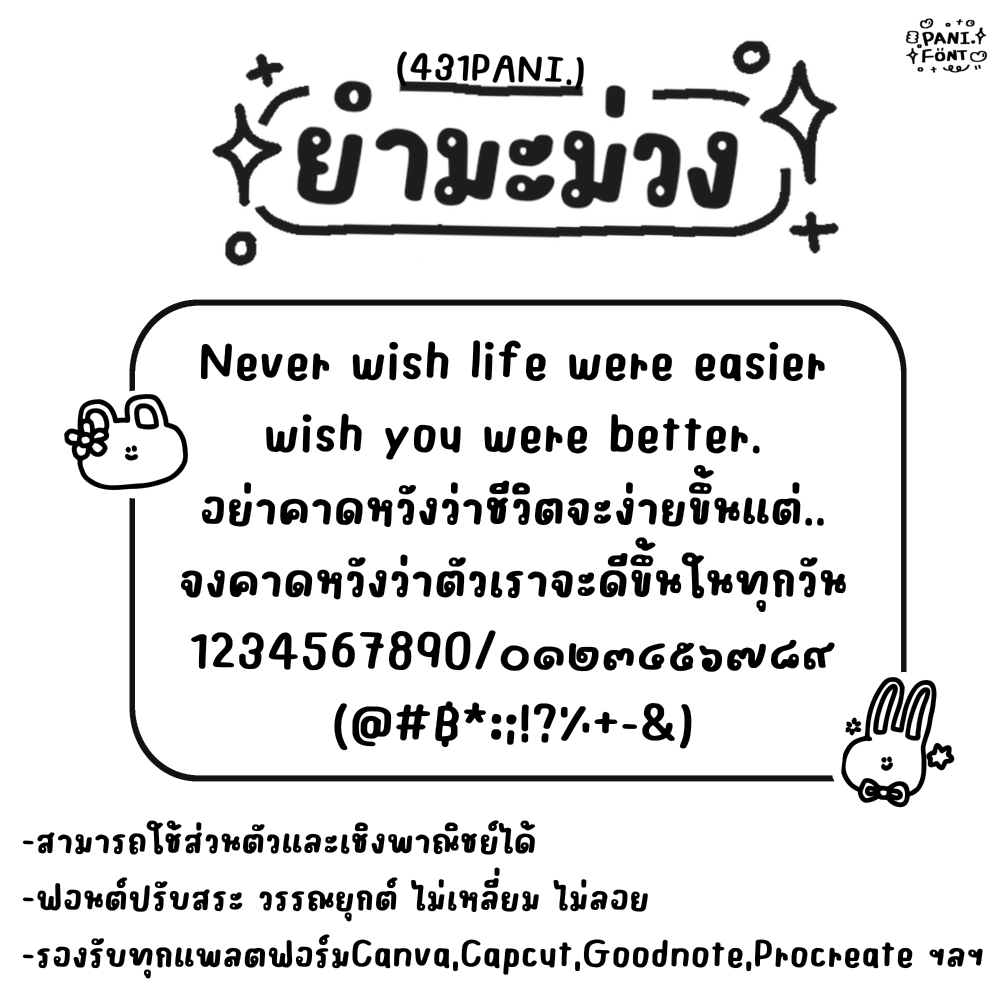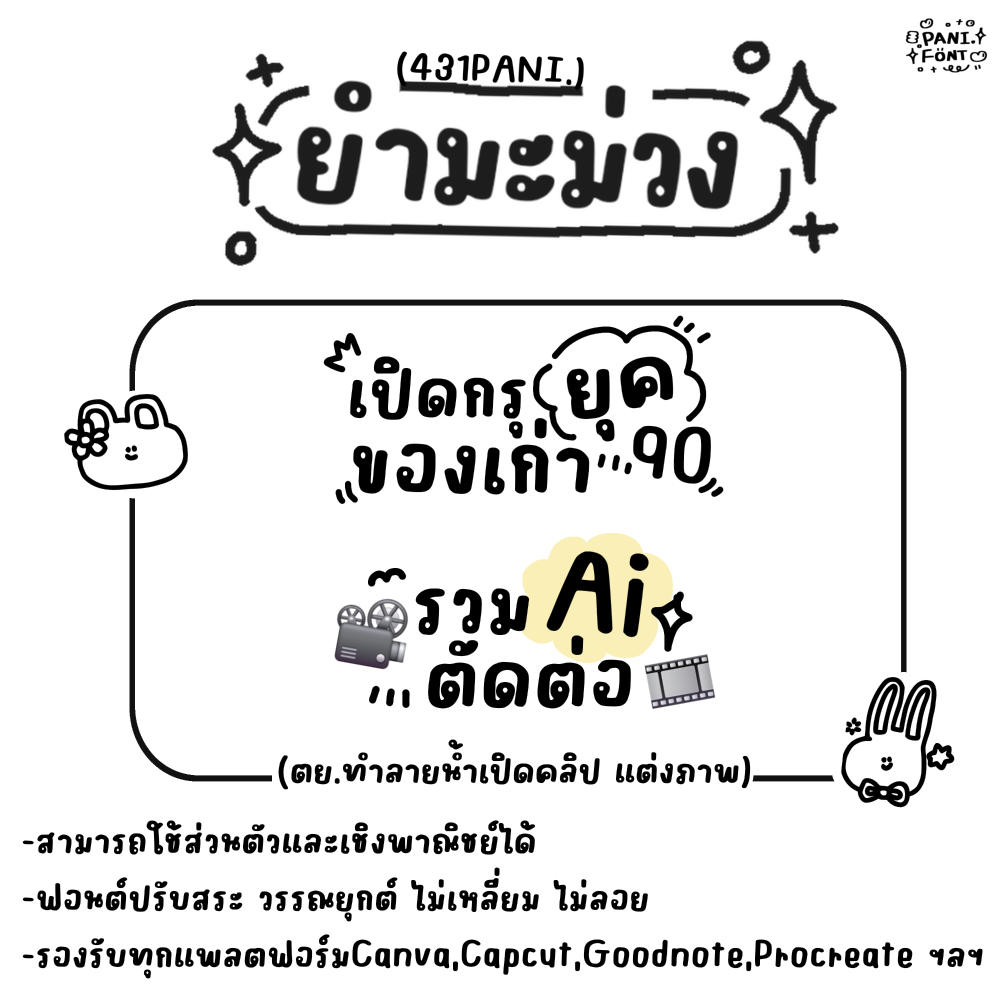
ꔛฟอนต์ 431PANI.ยำมะม่วง
ฟอนต์ตัวเข้ม หัวกลม ใช้งานง่าย มือใหม่ก็ใช้ได้
เด่นสะดุดตา ไม่ต้องขยับเยอะก็สวย เหมือนมืออาชีพ
ฟอนต์มี 3 ไฟล์ - น้ำหนัก บาง ปกติ หนา